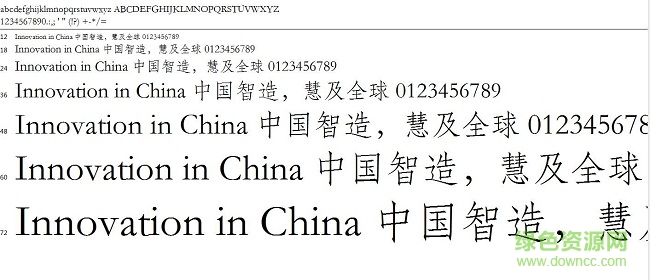
stfangsong.bold/常规体
stfangsong.ttf字体是一款华文仿宋字体,包含了粗体和常规体两款,现在的书籍印刷排版基本都是用宋体,仿宋用得很少,不过政府公文上仿宋体就比较多见了,有需要的朋友欢迎下载!
仿宋字体评价
仿宋是主要的中文字体之一,但是它的使用频率并没有宋体、楷体高,而其实我们在电脑上面看到的仿宋是字体设计者根据古籍作品加工的,删去了一些细节,使得字体更加平滑,但是却失去了一些字体原型的风韵。